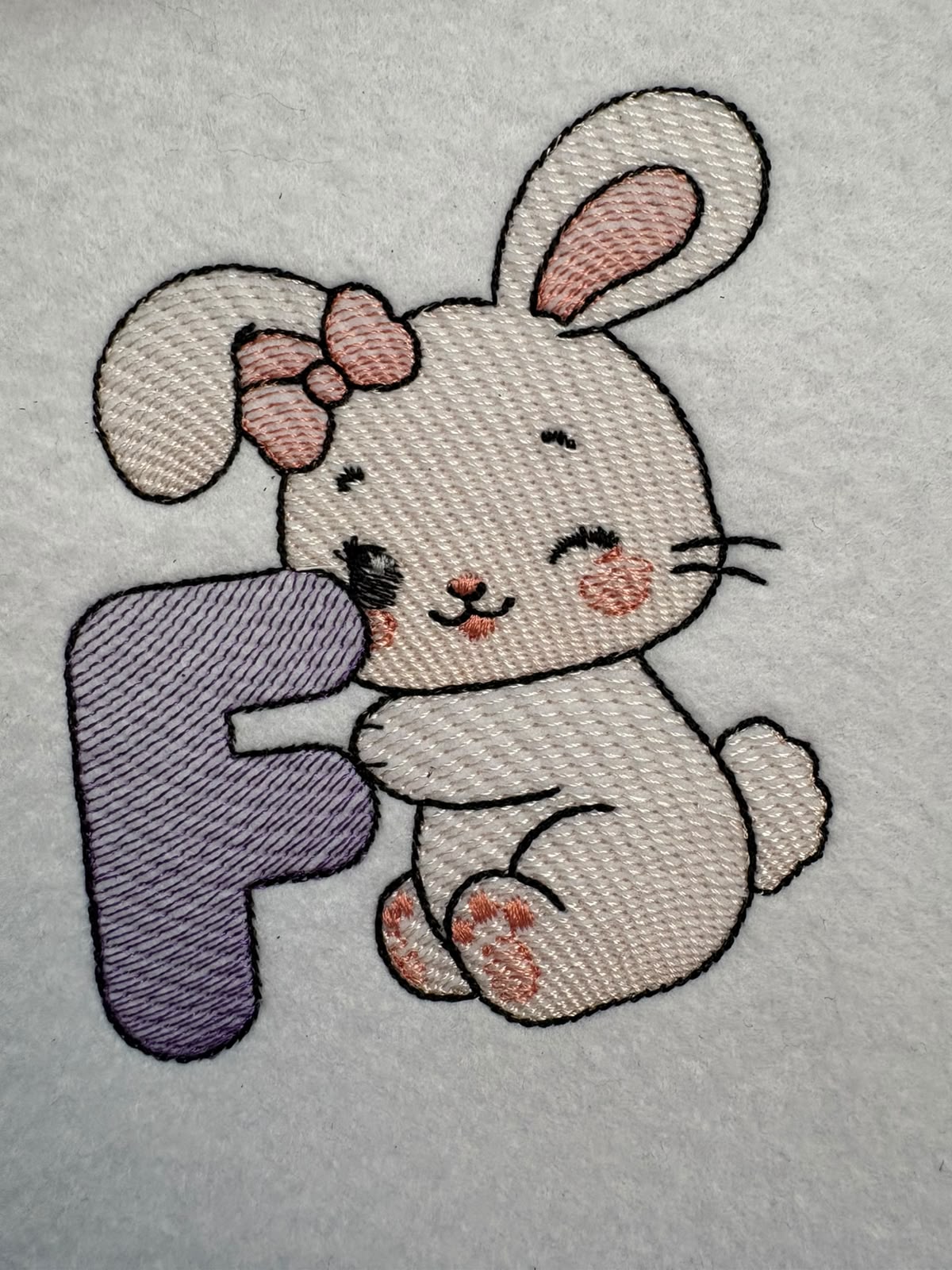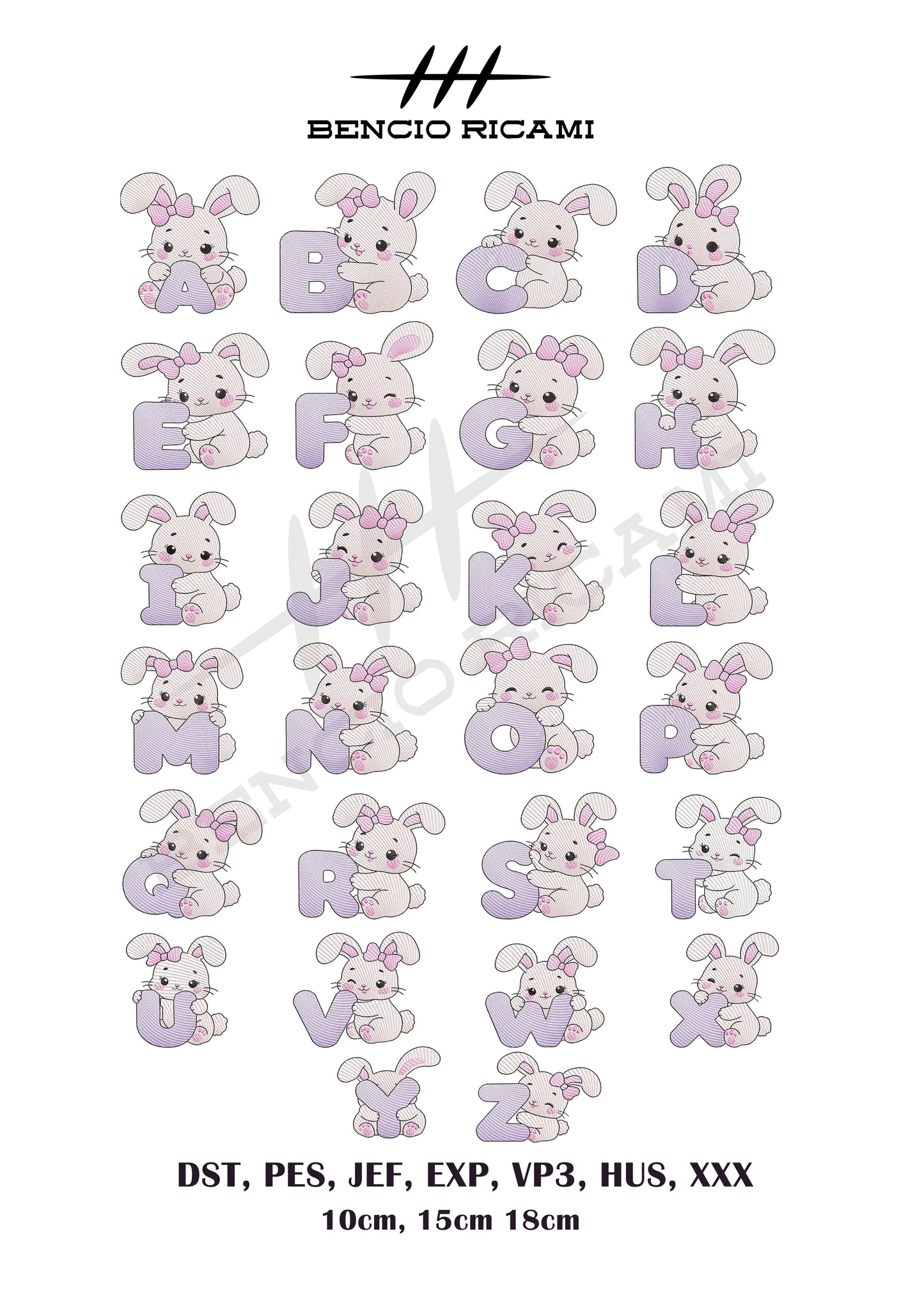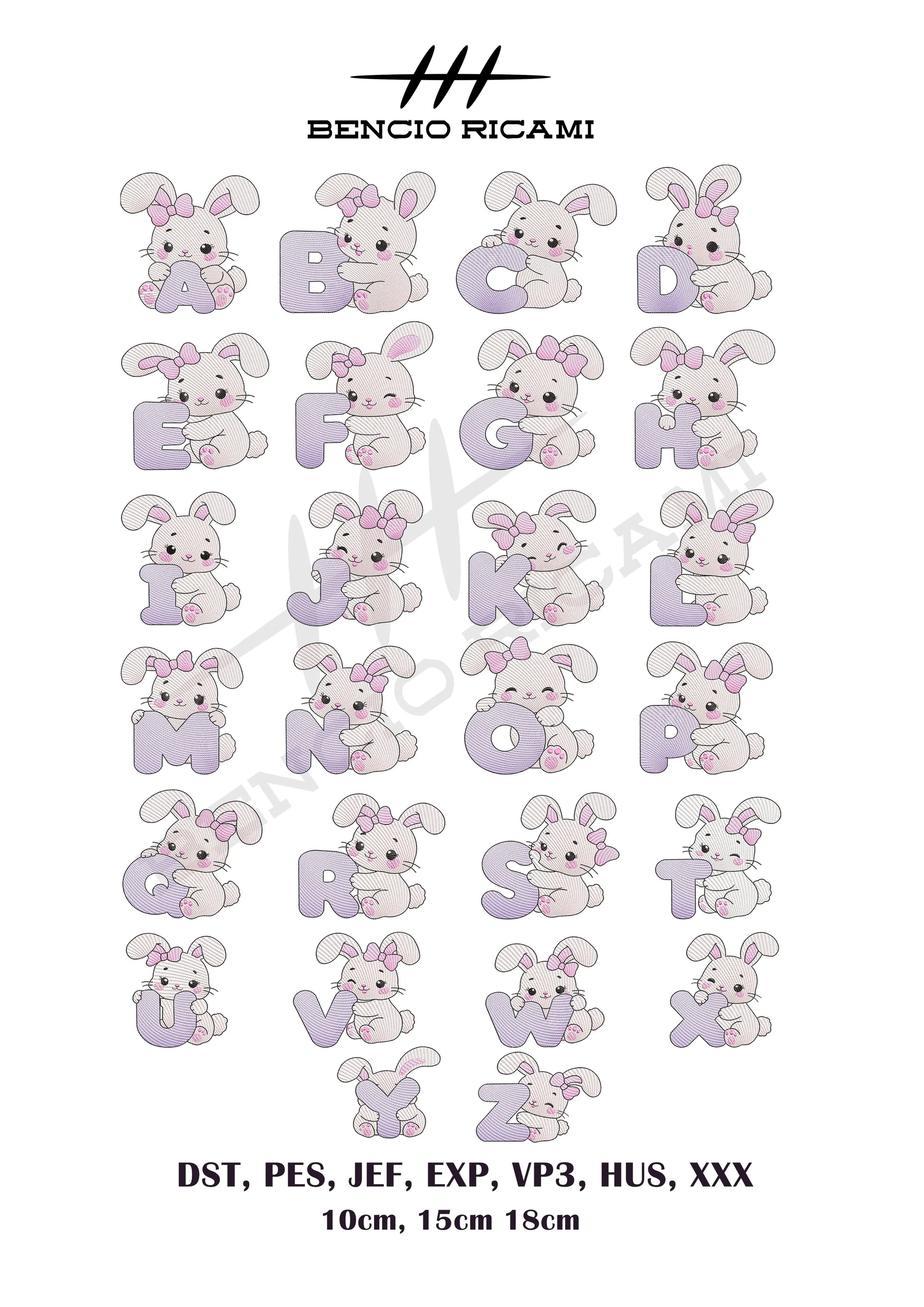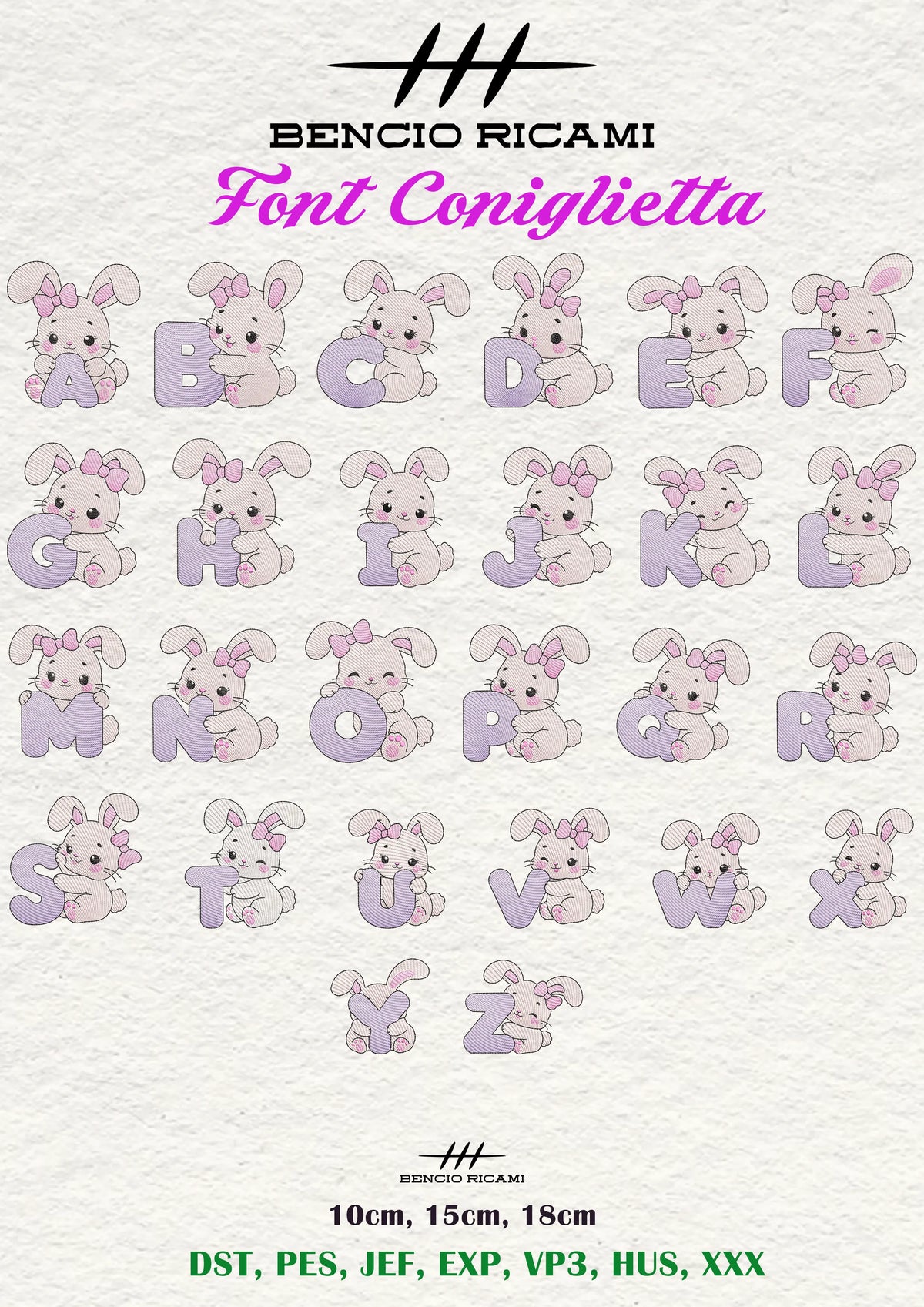
Font coniglietta - BencioRicami
File digitale da ricamo - Font Coniglietta
Aggiungi un tocco elegante e professionale ai tuoi ricami, un file raffinato perfetto per personalizzazioni su asciugamani, accappatoi, bavaglini, fiocchi nascita, abbigliamento, accessori e molto altro.
Il File è stato digitalizzato con attenzione ai dettagli per garantire un ricamo pulito e ben definito su diversi tipi di tessuto.
✅ Ricamo Dettagliato
✅ 26 lettere maiuscole con Coniglietta